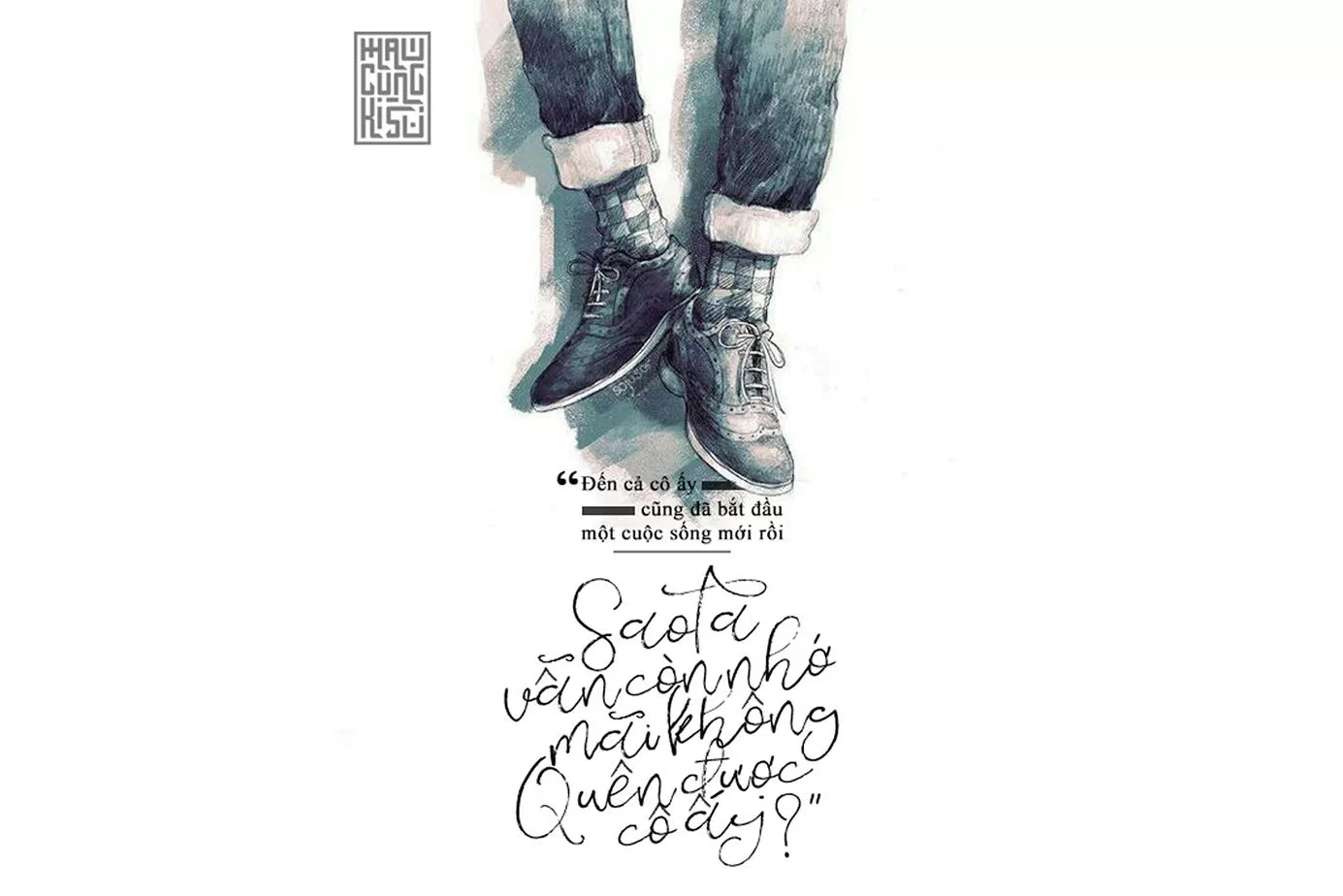
MTD Verona Lotte Việt hóa - Font chữ Viết tay nguệch ngoạc
MTD Verona Lotte Việt hóa là một font chữ viết tay mang nét nguệch ngoạc đầy cảm xúc, tạo nên vẻ đẹp tự nhiên và có phần mộc mạc. Các đường nét của font gợi cảm giác như được viết vội bằng bút mực, hơi nghiêng nhẹ và bất đối xứng, tạo ra sự chân thật, gần gũi như đang đọc những dòng nhật ký cá nhân. Font đặc biệt phù hợp với các thiết kế mang tính tự sự, hoài niệm hoặc chất thơ như trích dẫn, bìa sách, poster tâm trạng hay sản phẩm nghệ thuật cá nhân.